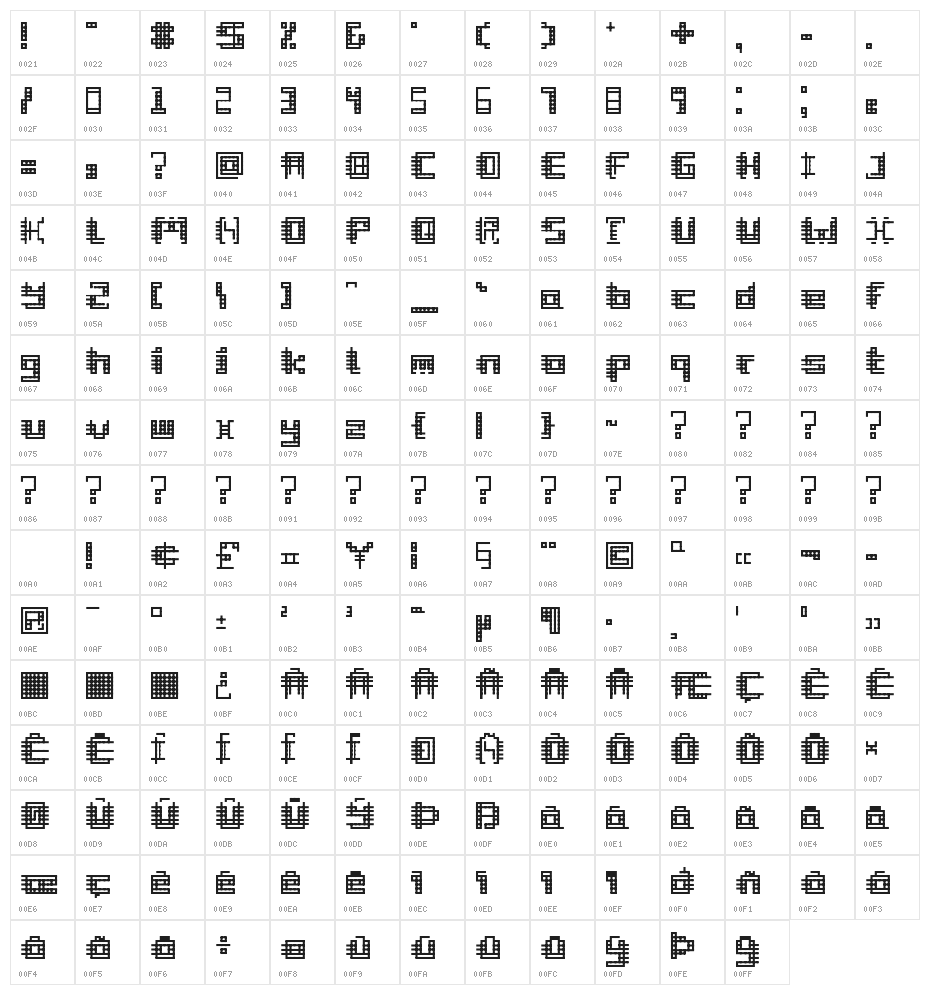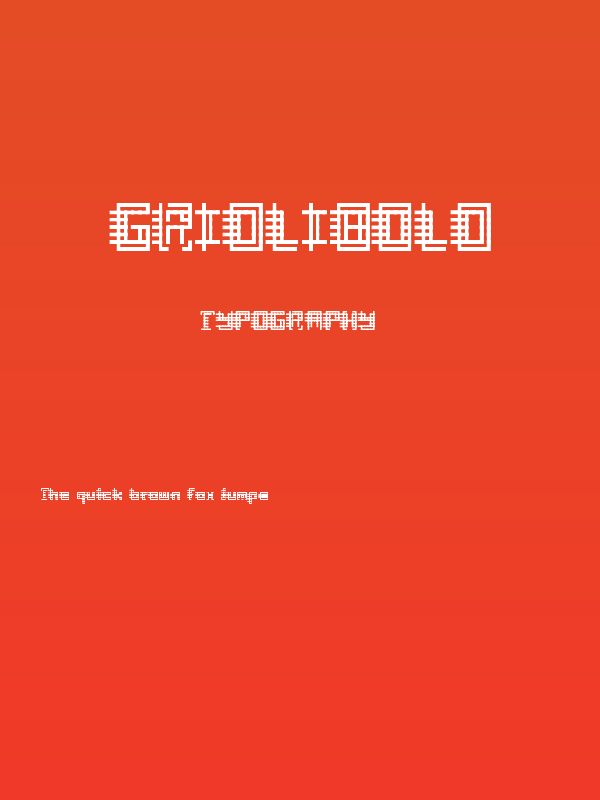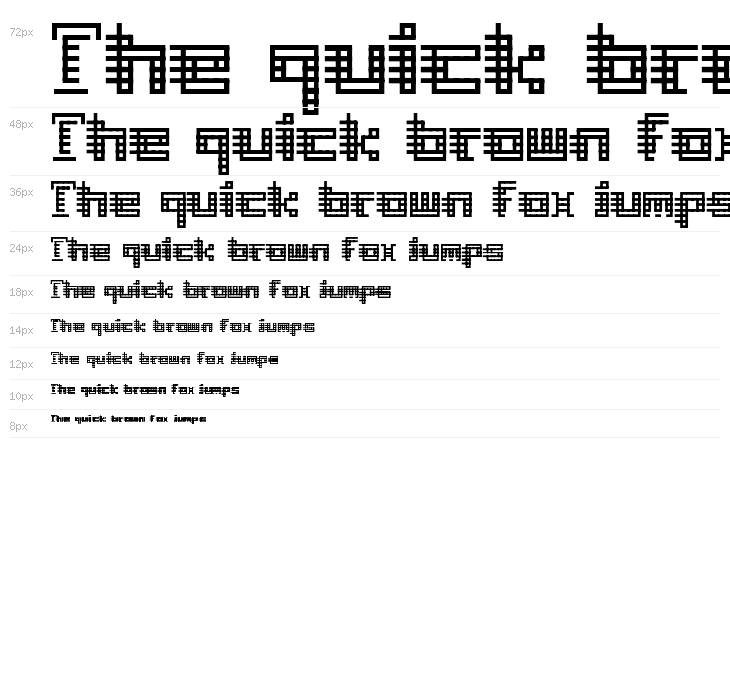
GridliBold Font
| Estilo geral | Retro, Digital |
| Projetos propostos | Ideal for digital art, retro-themed designs, video game graphics, and tech-related branding. |